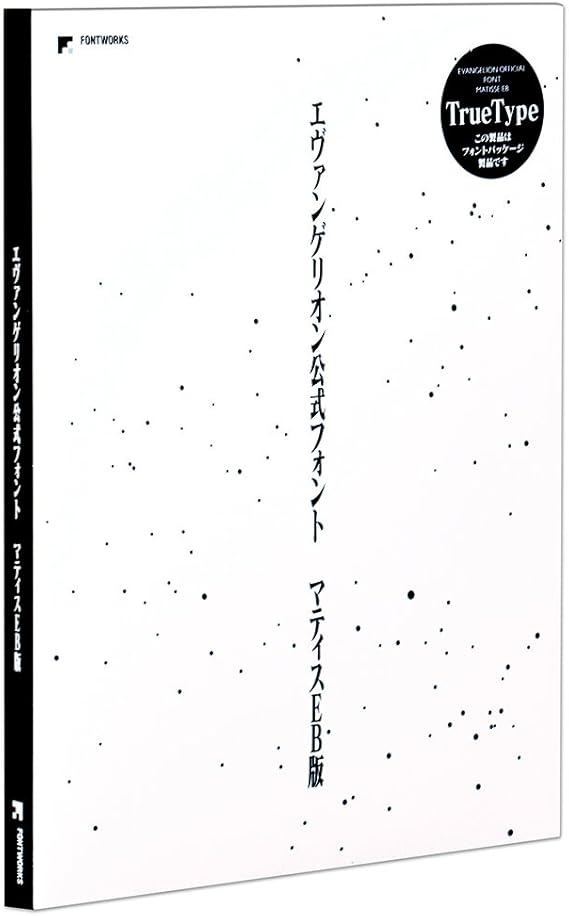
エレガントで高級でハイセンスなイメージのフォント。 Macユーザーは、始めから入っているので 常にデザインの選択肢として候補に入れるフォントです。 そして、実は似たフォントがほとんど無いという 書体なのです。これが本当に無い。.
マティスeb あの某有名アニメで使われたフォント。 「マティス」を選んで太字にチェックを入れると使うことができます。 黒背景に白字・赤字で雰囲気はバッチリ。 文字の大きさを変えたり、縦書き・横書きを組み合わせてみるとなおグッド!. 類似フォント その1「メイリオ」(マイクロソフト) Windows(Vista以降)に標準で搭載されている書体です。 個人的評価 新ゴに似てはいるのですが、何かが違う気がします。とはいえ、面倒な手間いらずに標準で使用できる点がグッド。. マティス(Matisse)は、フォントワークスが発売した明朝体およびそのフォント製品。 デザインはロダンを手がけた佐藤俊泰による。 1991年にMacintosh DTP用PostScriptフォントとしてリリースされた。.
エヴァフォント「マティスProEB」には無料ダウンロードはありません。 フリーフォントでも「極太明朝体」はありません。 エヴァファンなら「マティスProEB Truetype版」がベスト。 有料フォントを格安で購入するなら「AR 明朝体U」がおすすめ。. 「マティス Pro」で「太字」にチェックを入れると使用できますよ。 使い方 「CloudAlpaca」を起動するとクラウドサービスのウィンドウが表示。 ここでログインをしないとフォントワークスのフォントは使えません。 テキストの入力画面はこんな感じ。. さっそく日本語のフリーフォントで商用利用可能なものを教えてもらいました。ゴシック・明朝から手書き風まで、49種のフォントをご紹介します。プロのデザイナーも使用するスゴいフォントがそろってます。 1 ゴシック系 m fonts.
確かに似ていますね。 ですが、「麒麟がくる」と「エヴァンゲリオン」のフォントは違うようです。 エヴァンゲリオンで使用されているフォントは 「マティス」 になります。 麒麟がくるのフォントを「マティス」にして、比較したツイートがありました。. 今回は、CC以降のIllustratorのテキスト関連の機能強化や微調整についてまとめてみます。 「よく使うフォントをスピーディに選択したい」というフォント選択だけでも、大きく手が入っていますので、棚卸しとしてご一読ください。 チェックリスト Illustrator CC以降、変わったことを棚卸しする. このフォントはエヴァ公式フォントとして発売されています。 Amazon フォントワークス エヴァンゲリオン公式フォント マティスEB Truetype版 楽天 エヴァンゲリオン公式フォント マティスEB Truetype版() しかし、購入すると、そこそこのお値段します。.
エヴァフォントはマティスという有料フォントです。 しかし、WINDOWSの付属フォントを使用し、似たようなフォントにする方法はあります。 13年03月09日 投稿. フォント書体 Gotham は、現在流行中のもっとも人気のある、サンセリフ書体のひとつです。 デザイナー Tobias FrereJones 氏がフォントベンダー Hoefler & Co 所属時に、「力強くて、新しくて新鮮な」(英 Masculine, new, and Fresh)文字をコンセプトに、ニューヨークの街並みで見かける建物や看板などの. マティスではないけど、似たようなフォントが使えるジェネレーターを見つけました。 generatortubudecocom selfinovation 1351.
きこりフォントに似てるフリーフォント まるっかなSw9 ver111 – ぱれったいぷ – BOOTH(同人誌通販・ダウンロード) 唯一無二のフォントなので、難しいですが、しいていえばまるっかなフォント。. (2/7追記) こんにちはゆむらです。 タイトル通りです。暇だったので調べてみました。 くろかね eb パズドラといえばこのフォント。 太めのエレメントの端をスパッと落とし、鉄のように黒く力強い雰囲気の中に、どこか優しさをもっている書体。. フォントコラム マティスEB 新世紀エヴァンゲリオンで行われた文字表現 ※本書体はmojimomangaには含まれておりません。ご注意ください。 インタビュー 週刊少年ジャンプ まんが制作環境のデジタル化について;.
マティスeb あの某有名アニメで使われたフォント。 「マティス」を選んで太字にチェックを入れると使うことができます。 黒背景に白字・赤字で雰囲気はバッチリ。 文字の大きさを変えたり、縦書き・横書きを組み合わせてみるとなおグッド!. (2/7追記) こんにちはゆむらです。 タイトル通りです。暇だったので調べてみました。 くろかね eb パズドラといえばこのフォント。 太めのエレメントの端をスパッと落とし、鉄のように黒く力強い雰囲気の中に、どこか優しさをもっている書体。.